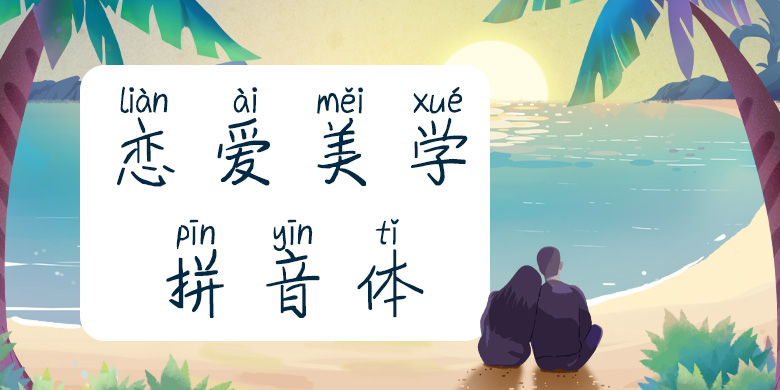
方正手迹-恋爱美学拼音体
字体品牌: 方正手迹 设计师:俞亦婷 字体分类:创意字体 字体属性:精品字 字符集:大陆简体(GB2312-80) 发布时间: 2018
恋爱美学拼音体的汉字部分天然稚拙,不做作,整个字有扑面而来的清新之感。适用于现代诗歌、短文的排版,以及屏显、影视综艺,及文化、商业类品牌的广告语设计。